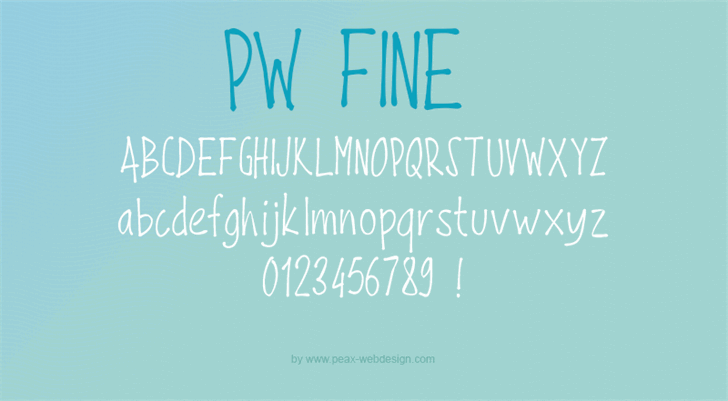
PW Fine Font
A PW Fine Font é uma fonte escrita a mão criada pelo designer Hamilton, ideal para projetos pessoais. Ela oferece um toque autêntico e único à sua identidade de marca ou projeto personalizado. Para uso comercial, o designer solicita que os usuários façam doações para continuar recebendo essa e outras fontes interessantes. Para se manter atualizado sobre novas fontes em desenvolvimento, Hamilton tem uma presença ativa no Facebook /fr-fr.facebook.com/peax.webdesign e no Google+ plus.google.com/103595703505477716588. Seja qual for o seu projeto, a PW Fine Font pode torná-lo ainda mais especial.